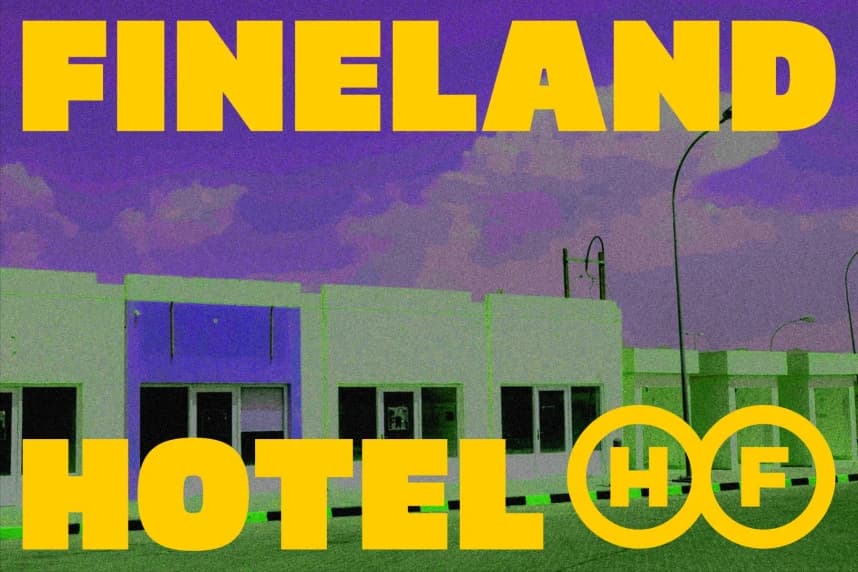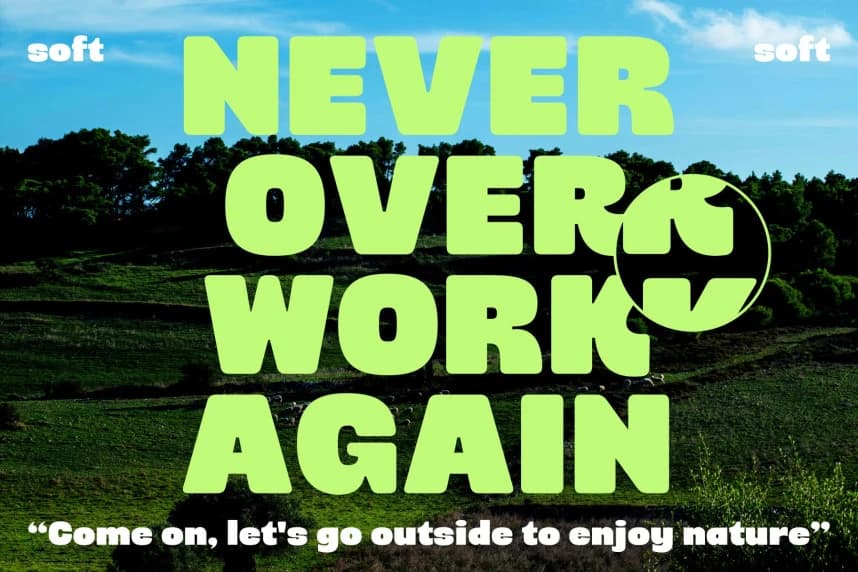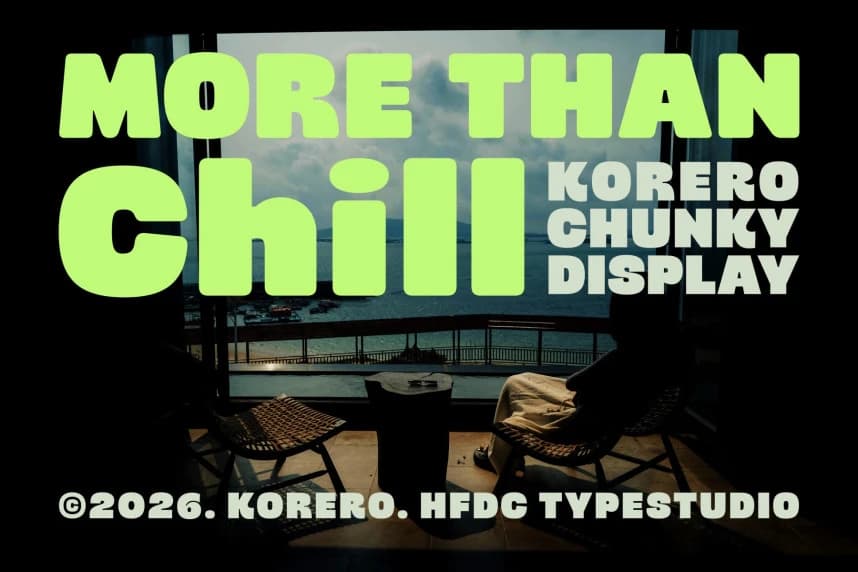
Korero Font
Korero Font, kalın çizgilere, sıkı harf biçimlerine ve kendinden emin bir görsel ağırlığa sahip cesur bir gösterim tipi yazı tipidir. İsmi, Maori dilinde 'konuşmak' ya da 'söylemek' anlamına gelen kelimeden türetilmiştir — ve görsel olarak bu yazı tipi tam olarak bunu yapar: yüksek sesle konuşur ve
Korero Font, kalın çizgiler, sık harf biçimleri ve kendinden emin bir görsel ağırlık etrafında şekillendirilmiş cesur bir display yazı tipidir. İsim, Māori dilinden “konuşmak” veya “sohbet etmek” anlamına gelen kelimeden türetilmiştir — görsel olarak bu font tam olarak bunu yapar: yüksek sesle konuşur ve her boyutta dikkat çeker.